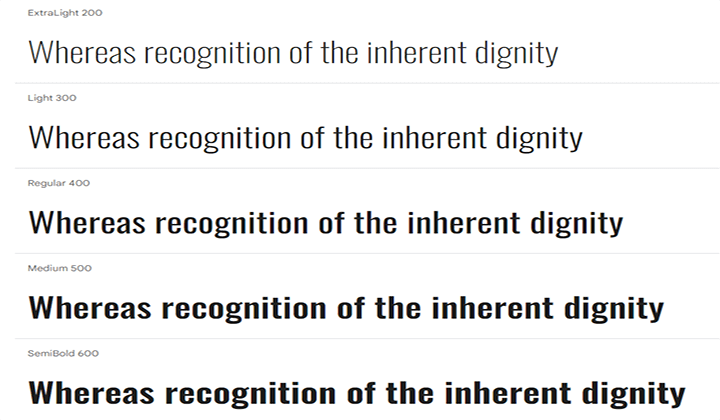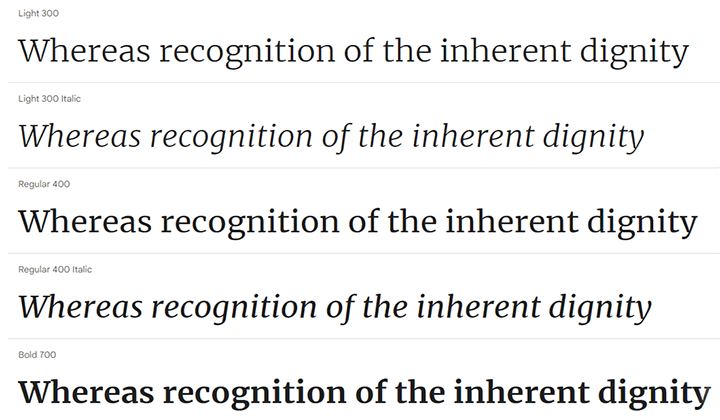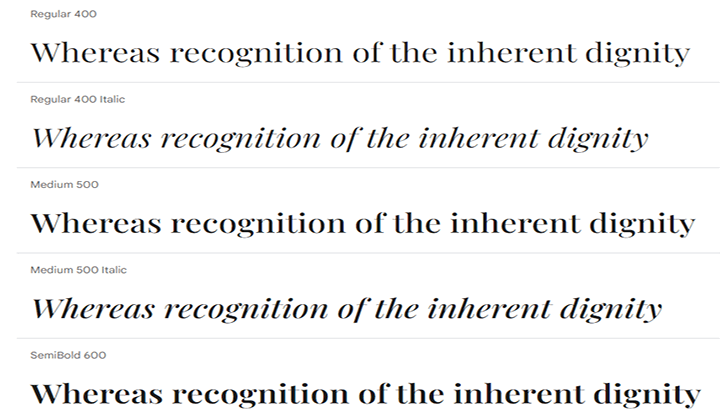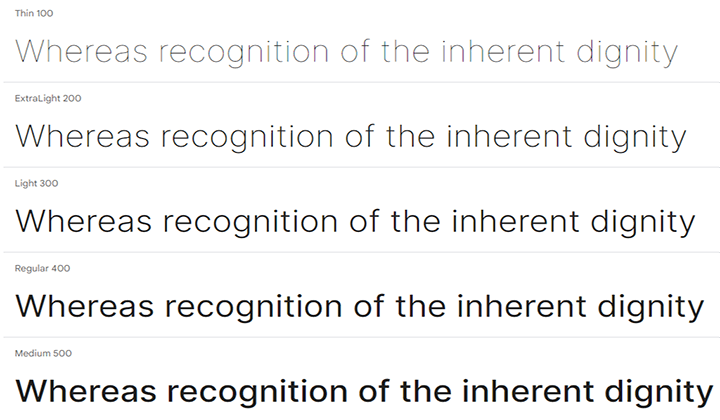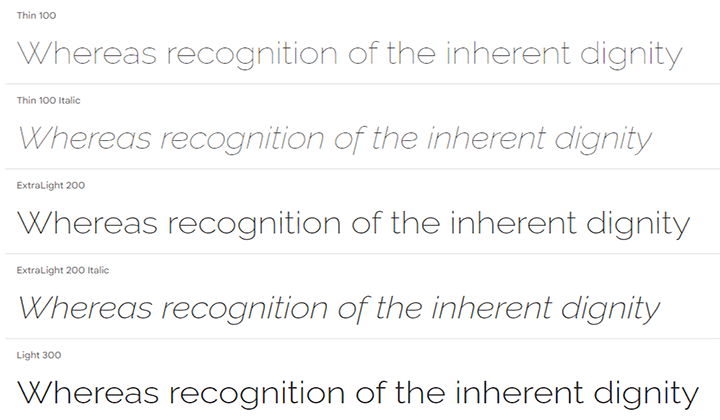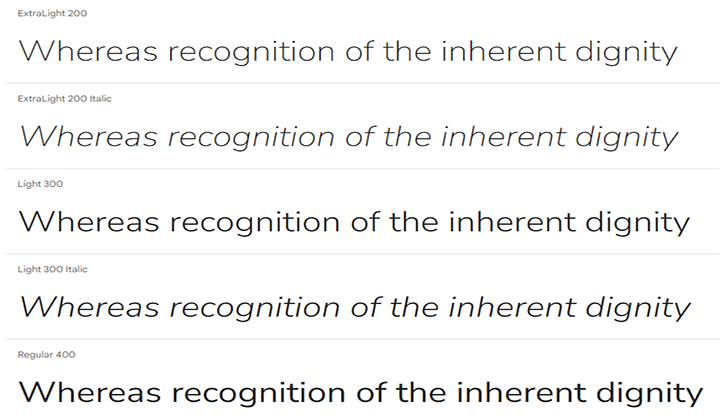
Cele mai bune 14 fonturi Google pentru a-ți îmbunătăți aspectul site-ului în 2024
Publicat: 2024-03-16Doriți să vă îmbunătățiți site-ul web cu fonturile Google ideale? Consultați selecția noastră aleasă cu atenție cu cele mai populare și versatile fonturi pentru a îmbunătăți lizibilitatea și experiența utilizatorului site-ului dvs.
Fonturile sunt ca niște eroi necunoscuți pentru a crea un site web atrăgător din punct de vedere vizual. Aceștia pot da tonul site-ului dvs. și pot transmite mesaje cu cea mai mare claritate.
Din fericire, fonturile Google au apărut ca un instrument esențial pentru designeri și dezvoltatori. Vine cu o selecție diversă de fonturi care vă pot ajuta să vă satisfacă nevoile.
Dar cu atât de multe opțiuni, care este cea mai bună pentru site-ul tău? Rămâi cu noi pentru a găsi fontul Google potrivit pentru site-ul tău.
În acest articol, am compilat cele mai bune fonturi Google care pot îmbunătăți lizibilitatea și estetica site-ului dvs.
Ce sunt fonturile Google și de ce ar trebui să le luați în considerare?
Google Fonts este o colecție gratuită și extinsă de fonturi web open-source furnizate de Google pe care le puteți utiliza pentru site-ul dvs. web. Iată câteva motive pentru care ar trebui să le luați în considerare:
- Selecție vastă – Google Fonts oferă o gamă diversă de fonturi de la clasic la modern, care includ atât Serif, cât și San Serif. Îl poți alege pe cel care se potrivește cel mai bine stilului site-ului tău.
- Optimizarea performanței – Fonturile Google sunt concepute special pentru utilizatorii web, asigurând încărcarea rapidă și eficientă a fonturilor pe diverse browsere și dispozitive și oferind utilizatorilor o experiență mai bună.
- Compatibilitate între browsere – Fonturile Google sunt proiectate să funcționeze bine cu diferite browsere web, asigurându-se că fontul arată același pe toate platformele.
- Actualizare regulată – Google își menține biblioteca actualizată adăugând regulat fonturi noi. Vă asigură că aveți acces la cele mai recente fonturi și tendințe de design, permițându-vă să mențineți o tipografie modernă și elegantă pe site-ul dvs.
Cele mai bune fonturi Google pentru site-uri web
| Numele fontului | Font | Suport lingvistic |
|---|---|---|
| Roboto | San Serif | 321 |
| Deschide Sans | San Serif | 575 |
| Montserrat | San Serif | 593 |
| Lato | San Serif | 399 |
| Poppins | San Serif | 252 |
| Oswald | San Serif | 583 |
| Noto Sans | San Serif | 866 |
| Merriweather | Serif | 252 |
| Afișarea Playfair | Serif | 531 |
| Inter | San Serif | 877 |
| Raleway | San Serif | 585 |
| Nunito Sans | San Serif | 612 |
| Ubuntu | San Serif | 317 |
| Rubik | San Serif | 560 |
| Work Sans | San Serif | 560 |
Roboto
Roboto este unul dintre cele mai populare și descărcate fonturi Google, concepute de Christian Robertson. Este un font versatil cu caracteristici duble.
Are o structură mecanică și geometrică cu curbe prietenoase și deschise. Permite literelor să-și mențină lățimea naturală, rezultând o experiență de citire lină și naturală. Vine în 12 stiluri diferite.
De asemenea, oferă familia de fonturi Roboto Condensed și Roboto Slab.
Deschide Sans
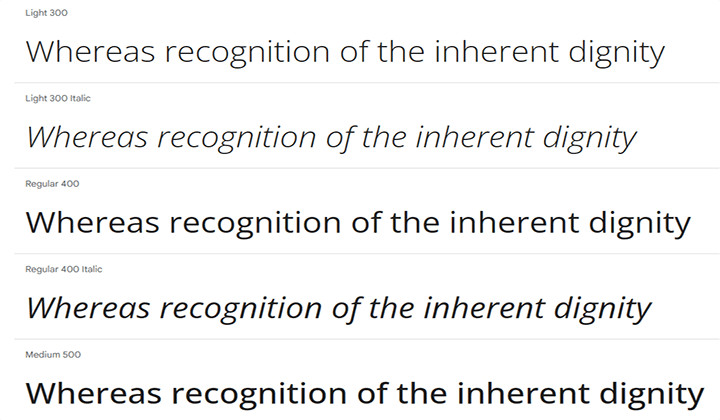
Open Sans este un font Google grozav conceput de Steve Matteson. Oferă o formă simplă, deschisă și un aspect prietenos, făcându-l modern și ușor de citit pentru o perioadă lungă de timp.
Funcționează bine cu imprimare, web și dispozitive mobile, ceea ce îl face o opțiune bună pentru diferite utilizări.
Oferă diferite greutăți, inclusiv ușoare, obișnuite, semi-îngroșate, extra îndrăznețe și lățime, inclusiv condensată, semi-condensată și normală.
Montserrat
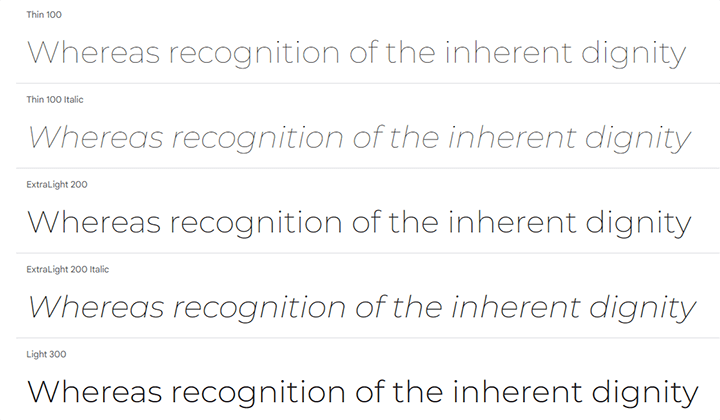
Montserrat este un font bine conceput și versatil, care vine cu diferite Greutăți. Julieta Ulanovsky a conceput acest font după ce s-a inspirat din afișe și semne vechi din cartierul Montserrat din Buenos Aires.
Scopul a fost salvarea esenței tipografiei urbane în prima jumătate a secolului XX. Cu familia sa obișnuită Montserrat, include și familii surori - Alternate și Subrayada.
Lato
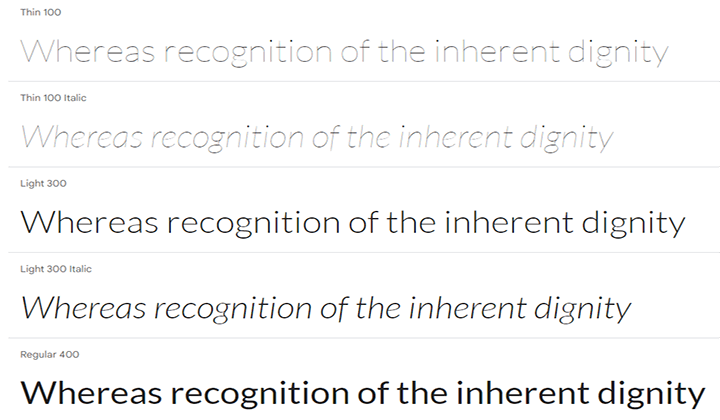
Lato este un font utilizat pe scară largă, conceput de Lukasz Dziedzic în vara anului 2010. Numele „Lato” înseamnă „vară” în poloneză.
A fost creat inițial pentru marile companii, dar ulterior a decis să se lanseze pentru toată lumea când compania a ales un stil diferit pentru identitatea sa. Oferă 10 stiluri care pot fi folosite în diverse scopuri.